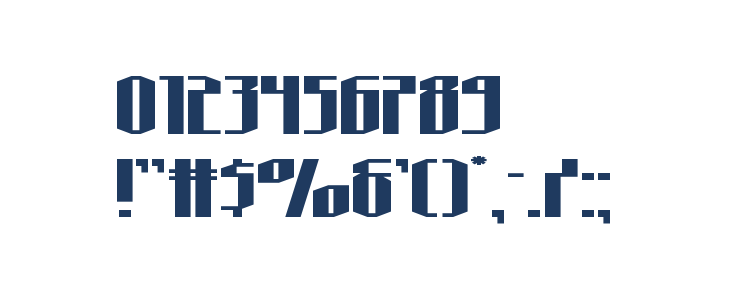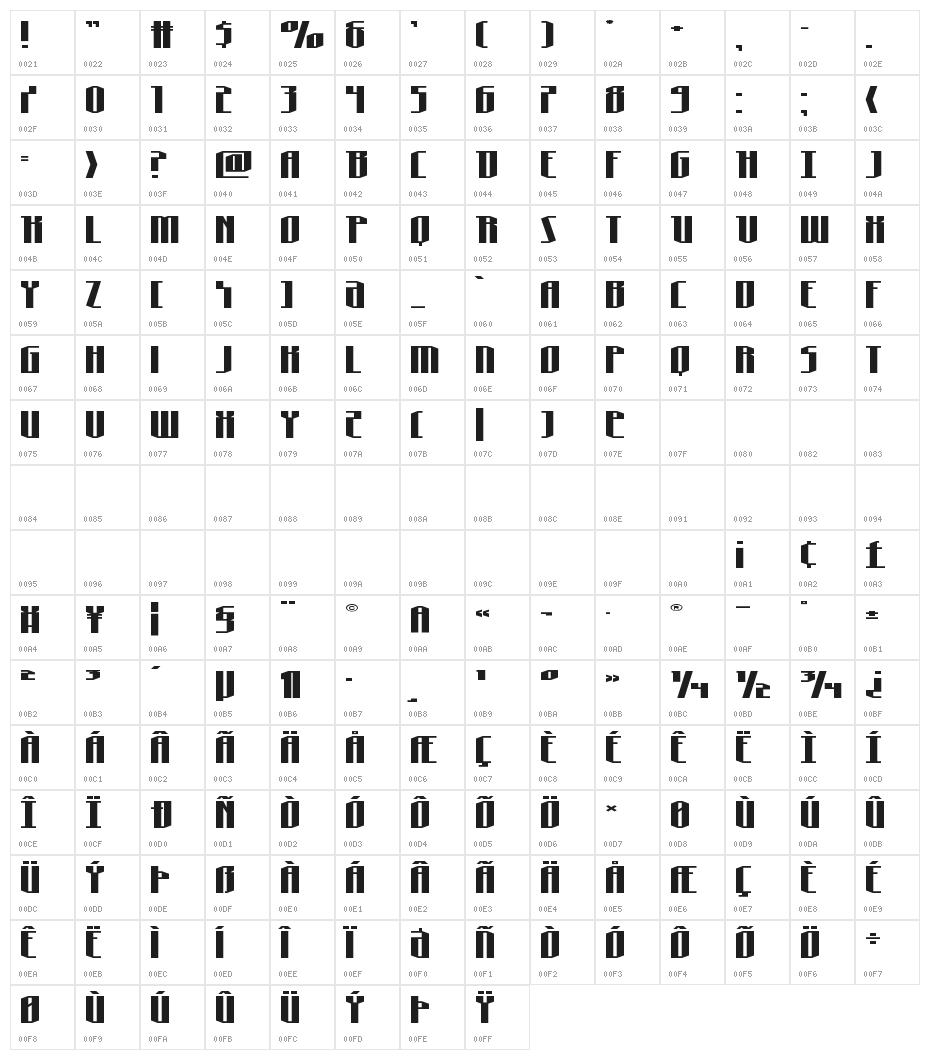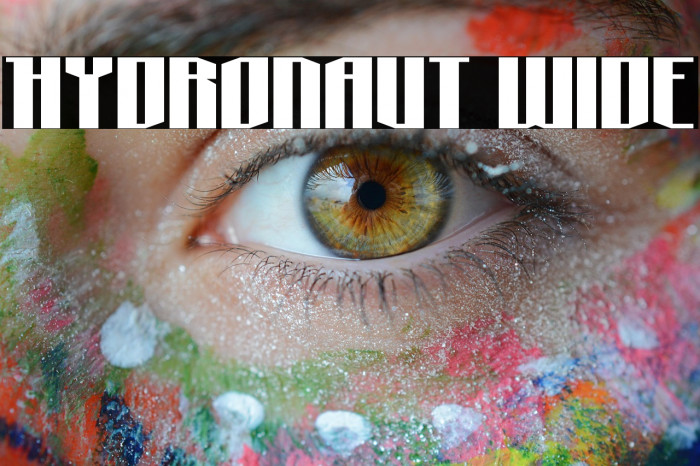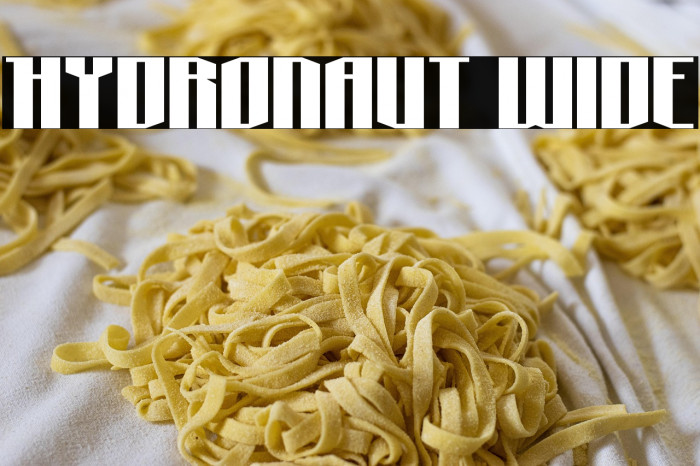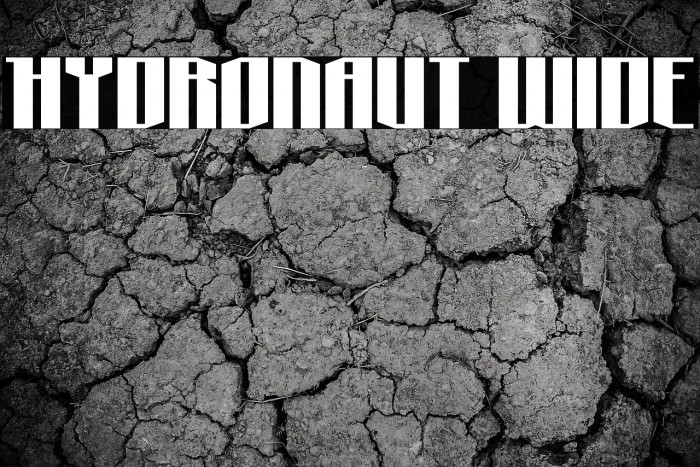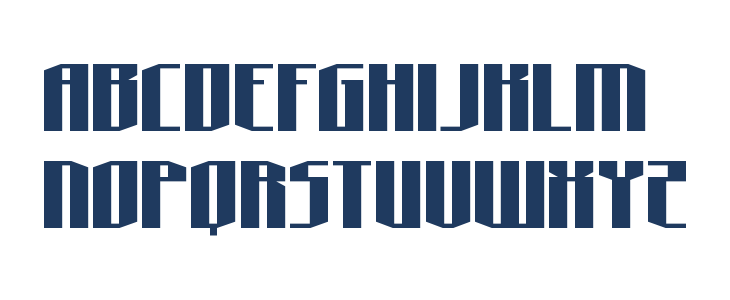
Hydronaut Wide Font
| Larghezza | Expanded |
| Stile generale | Futuristic |
| Progetti proposti | Ideal for sci-fi themed designs, video game titles, posters, and branding that requires a modern and bold statement. |